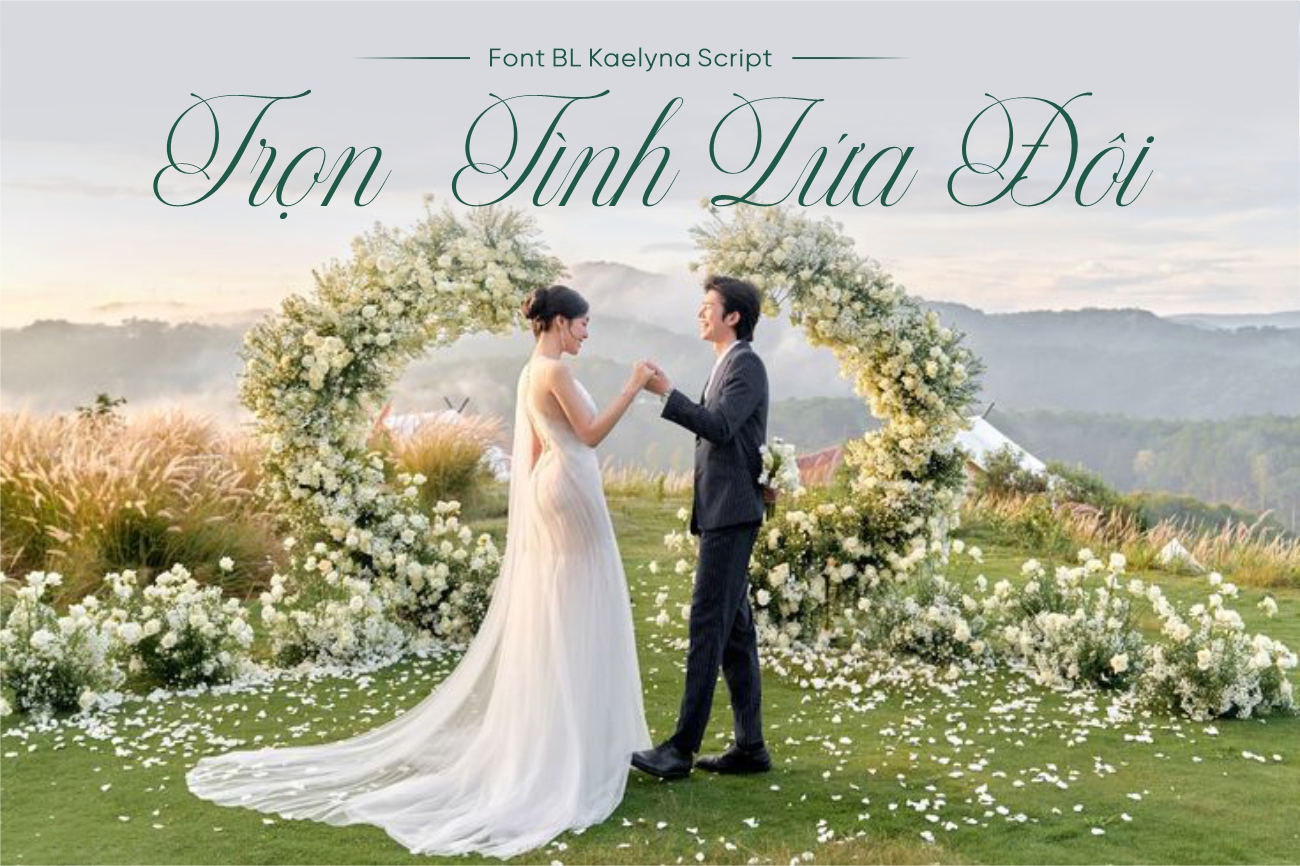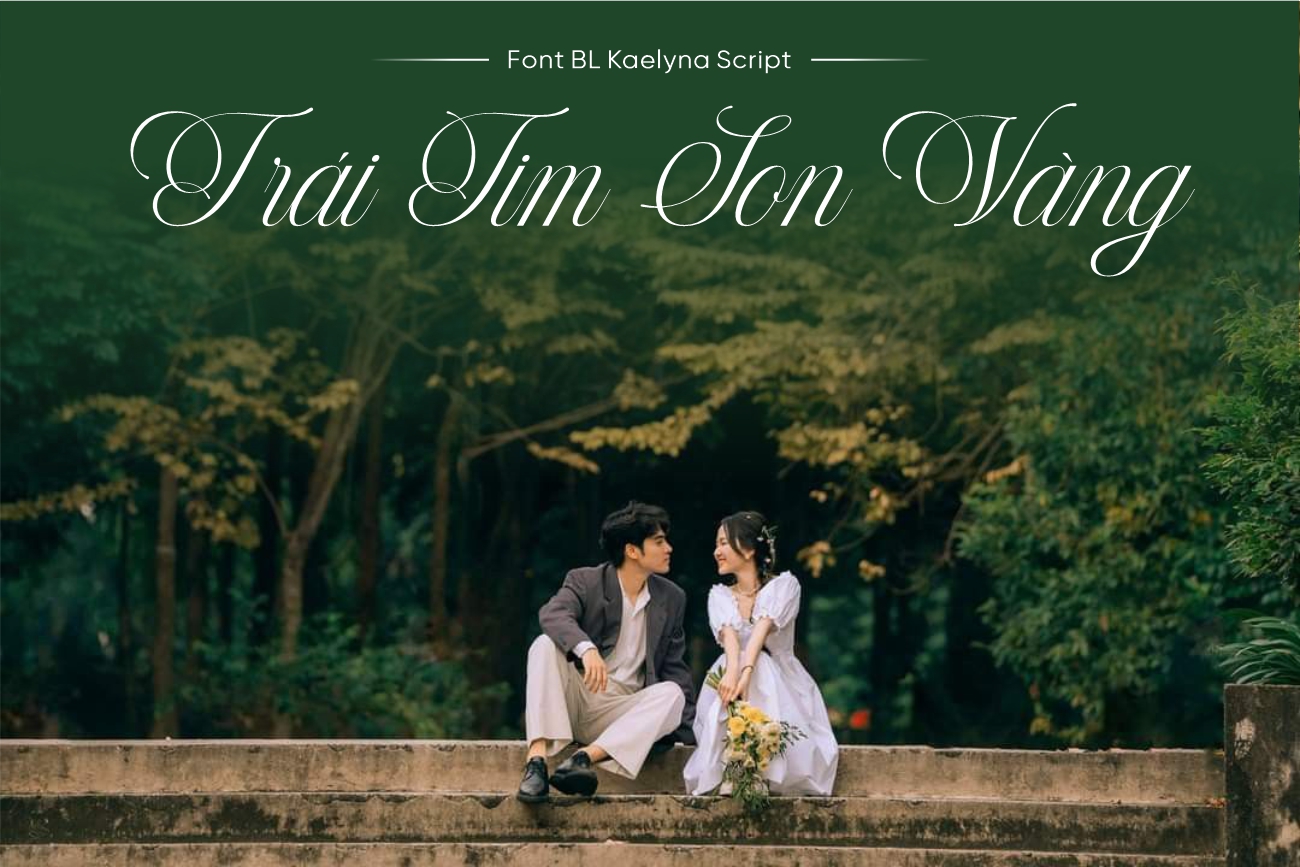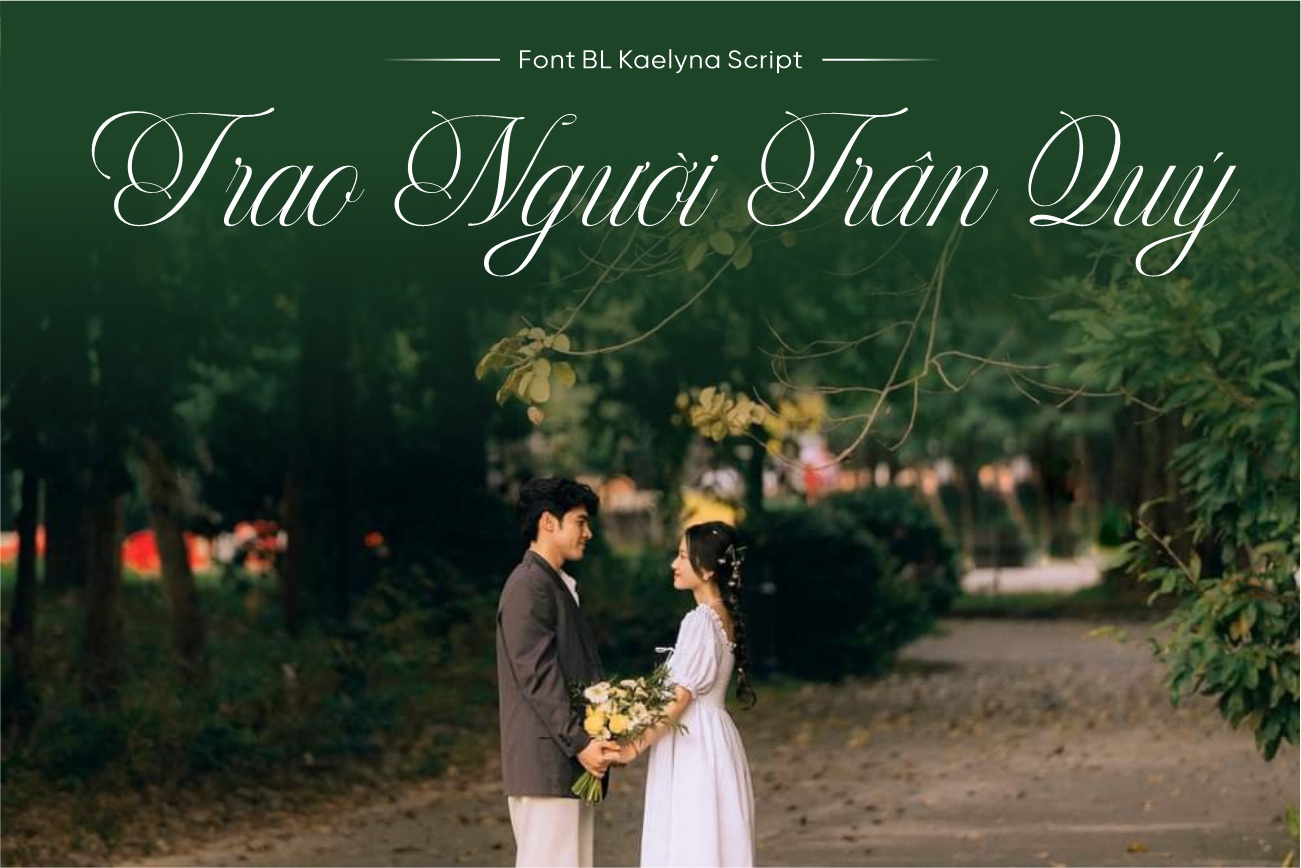
BL Kaelyna Script - Font thiệp cưới thanh lịch và sang trọng
BL Kaelyna Script là phiên bản Việt hóa từ bộ font Kaelyna Script do Pixesia Studio thiết kế, mang phong cách mềm mại, lãng mạn và giàu cảm xúc, rất phù hợp với các thiết kế cần sự tinh tế và trang nhã. Ngay từ cái nhìn đầu tiên, bộ chữ gây ấn tượng bởi những đường nét uyển chuyển, mượt mà như chữ viết tay được trau chuốt kỹ lưỡng. Team BL đã Việt hóa BL Kaelyna Script một cách tỉ mỉ, tối ưu hệ thống dấu tiếng Việt để các ký tự liền mạch, hài hòa và giữ được vẻ đẹp nguyên bản của font gốc, giúp người dùng Việt dễ dàng ứng dụng trong nhiều dự án thiết kế khác nhau.
Về kiểu dáng, BL Kaelyna Script sở hữu cấu trúc chữ mềm mại với độ cong tinh tế, các nét chữ nối liền tự nhiên tạo cảm giác bay bổng nhưng vẫn rất cân đối. Tổng thể bộ chữ toát lên vẻ dịu dàng, nữ tính và sang trọng, đúng tinh thần của một font thiệp cưới thanh lịch và sang trọng. Các đường nét được xử lý gọn gàng, không quá cầu kỳ nhưng đủ tinh xảo để tạo điểm nhấn thị giác, giúp nội dung trở nên nổi bật mà không gây rối mắt. Chính sự hài hòa này khiến BL Kaelyna Script đặc biệt phù hợp cho thiệp cưới, thiệp mời, backdrop lễ cưới, bảng tên cô dâu chú rể hoặc các ấn phẩm trang trí mang không khí lãng mạn.
BL Kaelyna Script không chỉ phù hợp với thiết kế cưới hỏi mà còn được ứng dụng hiệu quả trong các lĩnh vực thời trang, mỹ phẩm, thiệp chúc mừng, logo thương hiệu cá nhân hoặc các dự án cần truyền tải cảm xúc nhẹ nhàng và tinh tế. Nhờ phong cách mềm mại nhưng vẫn chỉn chu, bộ chữ giúp nội dung trở nên gần gũi, trang nhã và dễ tạo thiện cảm với người xem. Khi sử dụng đúng bối cảnh, font phát huy tối đa vai trò của một font thiệp cưới thanh lịch và sang trọng, góp phần nâng tầm giá trị thẩm mỹ cho tổng thể thiết kế.
Nguồn gốc của Kaelyna Script xuất phát từ cảm hứng về vẻ đẹp lãng mạn và tinh thần của những khoảnh khắc đáng nhớ trong cuộc sống. Khi được Team BL Việt hóa thành BL Kaelyna Script, bộ font không chỉ giữ trọn cá tính thiết kế của Pixesia Studio mà còn trở nên thân thiện hơn với người dùng Việt nhờ khả năng hiển thị tiếng Việt mượt mà, chuẩn xác. Nếu bạn đang tìm kiếm một kiểu chữ vừa mềm mại, vừa tinh tế, đúng chuẩn font thiệp cưới thanh lịch và sang trọng, BL Kaelyna Script chắc chắn sẽ là lựa chọn lý tưởng để tạo nên những thiết kế giàu cảm xúc và đầy ý nghĩa.